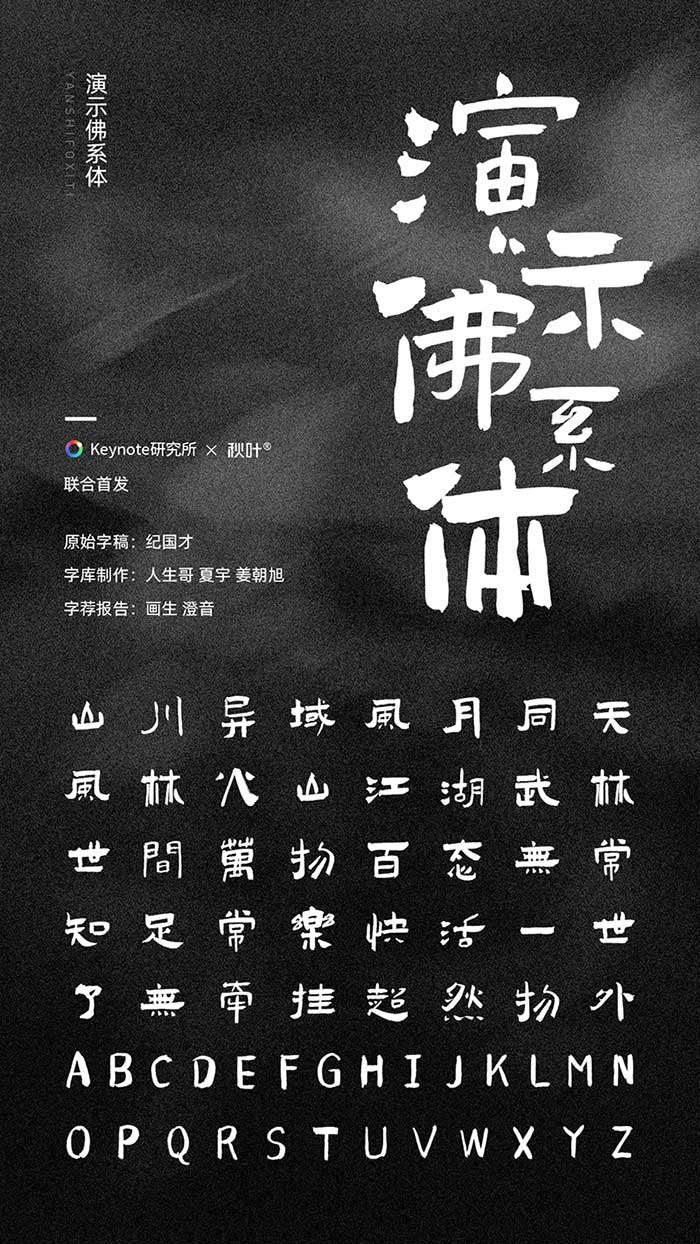
演示佛系体由酷爱书法的纪国才老先生,在80岁这年亲手写了一套独具风格的字体,并授权 Keynote研究所 和 秋叶PPT 面向全社会联合首发,全渠道免费商用!
纪国才老先生一生经历了风云更迭,字如其人,印刻着时光的痕迹,沉淀着岁月的厚重,也诉说着人生的洒脱,有种超然物外之态。
演示佛系体打破固有造字框架的条条框框,又有一致的内核,形散而神不散;演示佛系体不再是常规书法字体中怒放的飞白和笔触,将潇洒收敛,但也厚重有力;字体整体乍看之下,似以繁体字为主,但多看一些,才发现,诸多奇特的偏旁部首写法,是现代简体繁体都不具备的。